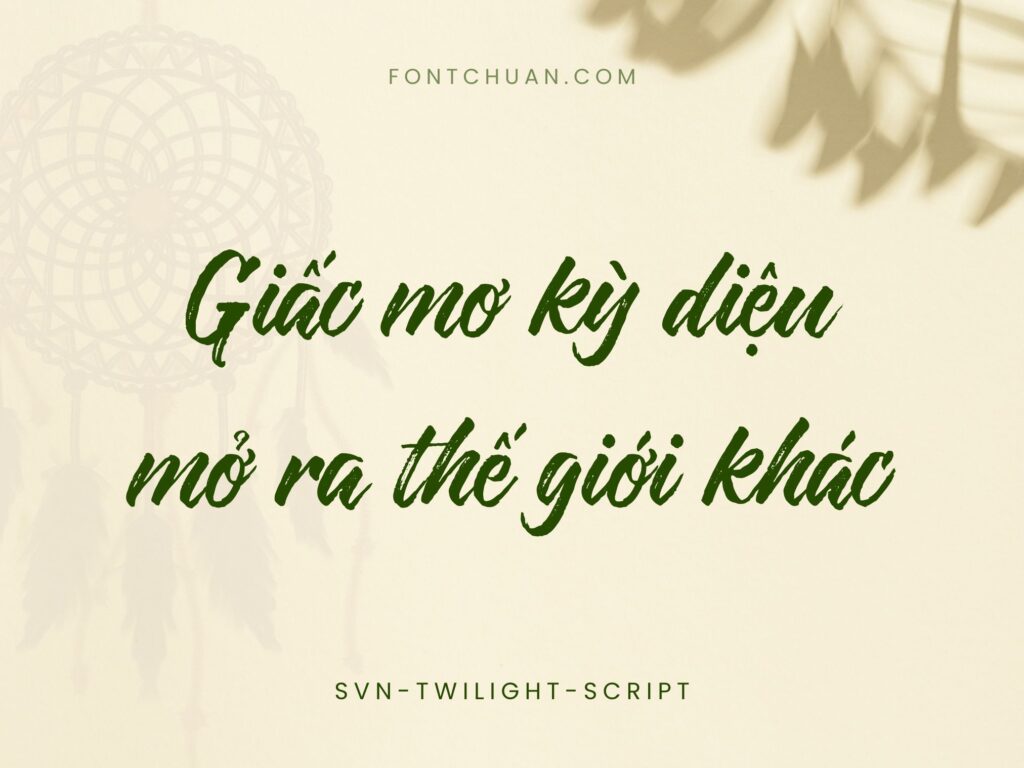
Font SVN Twilight Script Việt Hóa
Tác giả Font: Hermansyah Getstudio
Font SVN Twilight Script là phiên bản Việt hóa của kiểu chữ Twilight Script, được thực hiện bởi STYLEno.1 Fonts. Twilight Script là một Font Decorative với phong cách viết tay cọ khô, được thiết kế để kết hợp hoàn hảo và cho phép bạn tạo ra các tác phẩm chữ viết tay tuyệt đẹp một cách nhanh chóng và dễ dàng. Font này lý tưởng cho việc thiết kế logo, trích dẫn viết tay, bao bì sản phẩm, tiêu đề, áp phích, hàng hóa, truyền thông xã hội và thiệp chúc mừng.
SVN Twilight Script lý tưởng cho các dự án thiết kế yêu cầu sự cá nhân hóa và sáng tạo, như thiệp mời, logo, tiêu đề và các ấn phẩm truyền thông. Các ngành nghề như thiệp cưới, ẩm thực và spa có thể tận dụng font này để tạo điểm nhấn trong thiết kế. Ngoài ra, font cũng thích hợp cho các sự kiện như Tết, Valentine, Sinh nhật và các lễ hội khác.